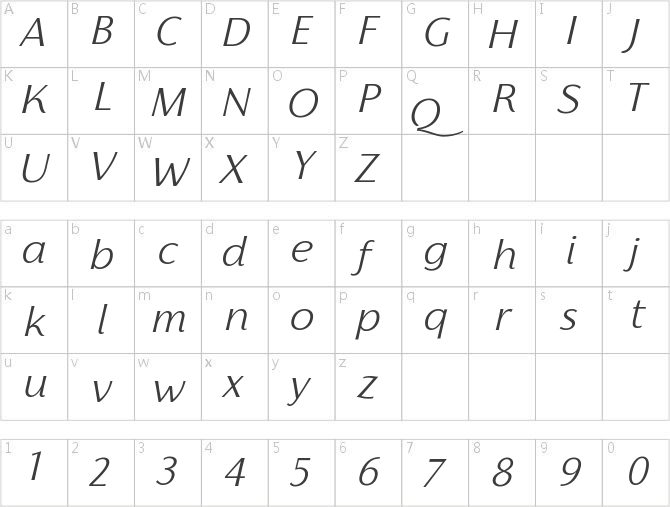
字體名稱: Florent
Florentia-Light-Italic-trial
Florentia-Light-Italic-trial字體字庫是一款讓人賞心悅目、百看不厭的英文字體,適合各類廣告和產品包裝設計應用,字體大小0.19MB,格式為ttf字體,上傳用戶是隨緣゜,作者/版權方為未知